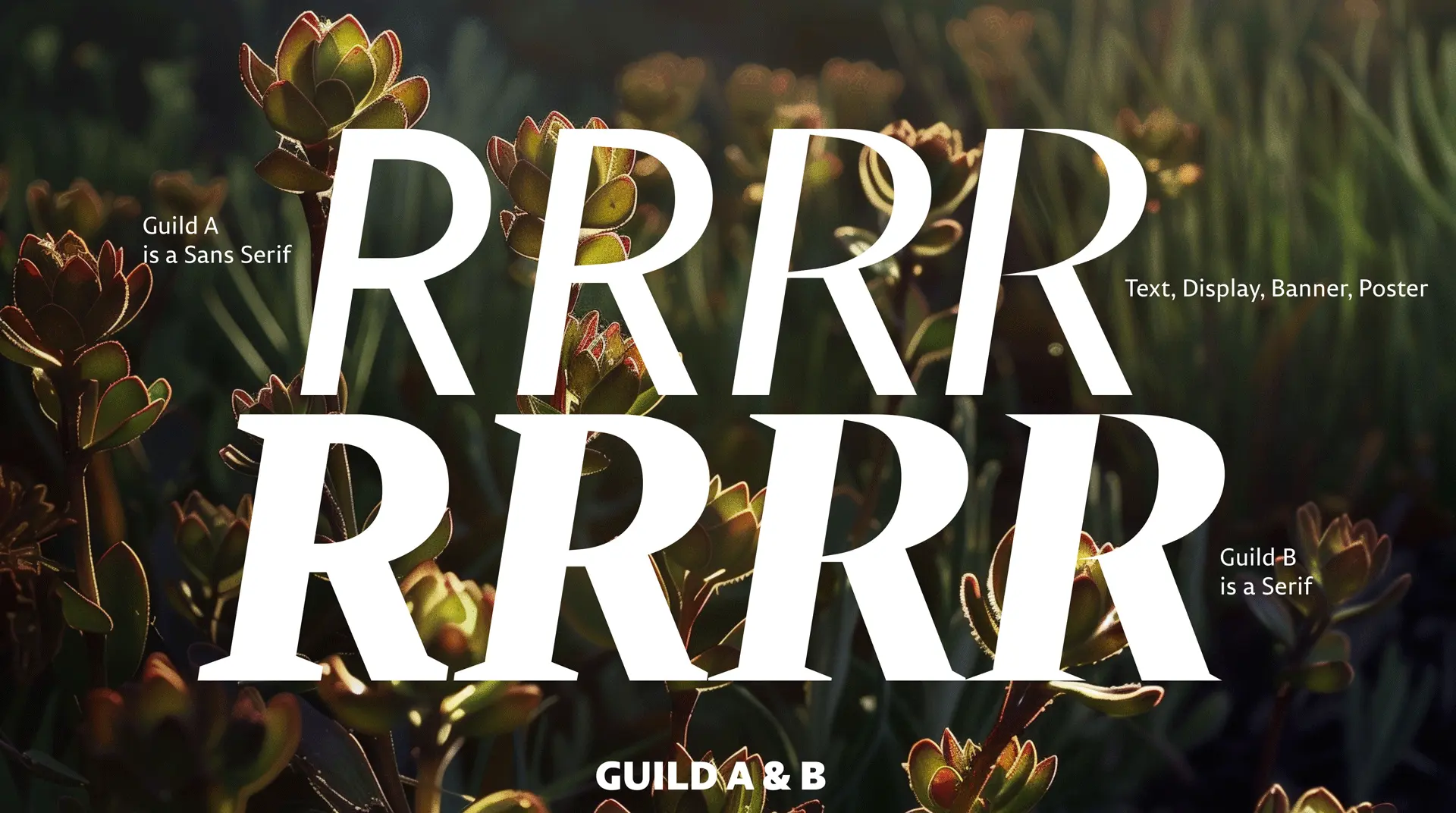
Guild — это обновлённая версия шрифта Permian, который Илья Рудерман рисовал для Перми почти пятнадцать лет
Через десять лет после того, как работа над глобальным ребрендингом Перми прекратилась, Permian решили обновить. За это, по приглашению студии CSTM Fonts, взялся выпускник курса «Шрифт и типографика» в Британской школе дизайна Толя Дудко. Он нарисовал текстовые начертания для гротеска (Guild A) и антиквы (Guild B), а от брусковой антиквы, которая была в Permian, в Guild решили отказаться.
Позже Илья Рудерман нарисовал ещё и дисплейные антикву и гротеск, увеличив в них контраст настолько, что в некоторых начертаниях гротеск превращается в ленточную антикву. Благодаря этому решению шрифт стал более характерным и актуальным, но остался достаточно универсальным и разносторонним для того, чтобы в одиночку решить дизайн-задачи целого города (или целой компании).
В кассе Guild — лигатуры, дроби, табличные цифры, верхние и нижние индексы, много знаков валют. Шрифт поддерживает расширенные кириллицу (включая болгарский, сербский и македонский) и латиницу (включая вьетнамский).